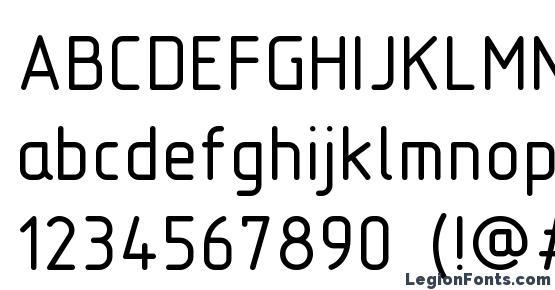
Шрифт гост тип б
Название: Шрифт гост тип б
ГОСТ 2.304-81
При переводе файлов Visio в PDF с использованием шрифта ГОСТ типа Б (GOST type B) изменяется вид документа самым разнообразным образом, но в.
Каждому Чертежу Сопутствуют Надписи. Начертание Букв И Цифр.
7 мар. 2018 г. Шрифт по ГОСТ 2.304-81 Тип А и Тип Б включает все знаки пункта 7, плюс наиболее распространенные математические дроби. Версия наклонного и.
2; тип Б с наклоном около 75° (d= V\q К) с параметрами, приведенными в табл. 2. Т а б л и ц а. 1. Шрифт типа A (d = ¥и.
Гостовские Шрифты Для Оформления Чертежей GOST Type A.Ttf И GOST.
Шрифты Чертежные (ЕСКД)
Шрифт GOST Type B Standard (Русский Шрифт)
GOST Type B Font
Тип Б с наклоном около 75о (d=h/10. Тип определяется параметрами шрифта: расстояниями между буквами, минимальный шаг строк, минимальное расстояние между.
ГОСТ 2.304—81 — Викитека
Шрифты Чертежные (ЕСКД)
Гостовские Шрифты Для Оформления Чертежей GOST Type A.Ttf И GOST.
тип Б с наклоном около 75° ( =1/10 ) c параметрами, приведенными в табл.2. Таблица 1. Шрифт типа A.
Основные Вопросы И Ответы По Работе: Чертежные Шрифты. Подборка.
14 сент. 2023 г. GOST type B – что это за шрифт и как им пользоваться. Шрифт Gost type b — это один из наиболее популярных шрифтов, используемых в России и.
При переводе файлов Visio в PDF с использованием шрифта ГОСТ типа Б (GOST type. В 1-м случае, шрифт ГОСТ типа Б не распознается Acrobat-ом и.